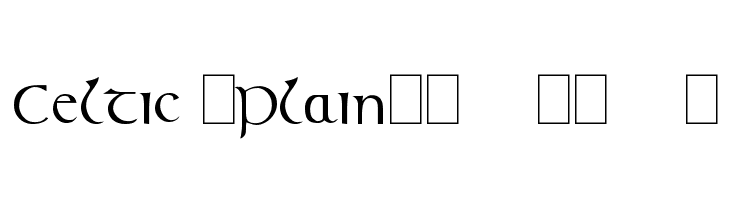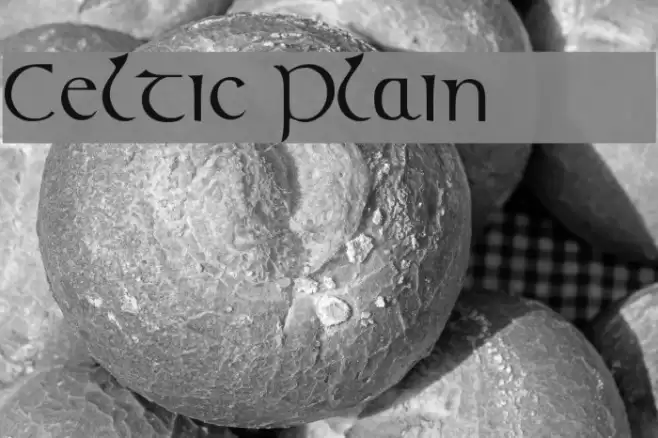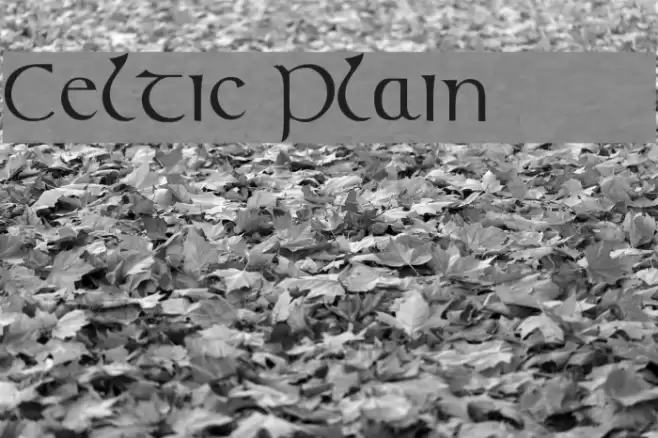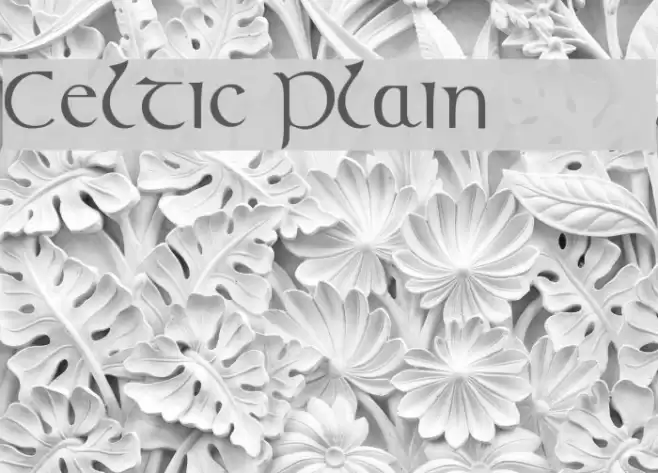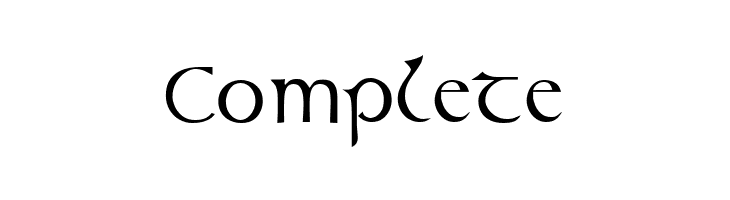
Celtic [Plain]:001.001 Font
| Proiecte propuse | Ideal for cultural or historical projects, book covers, posters, and branding that requires a touch of elegance and tradition. |